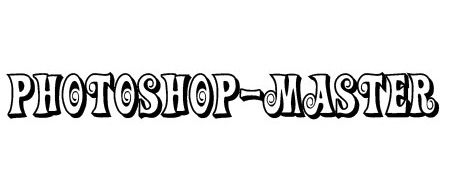
Шрифт супер!
COOOL))))))))))ХД
ХАХА СТИЛЬ РЕТРО!
шикарно!
Респект!
Супер!!!!!!!!!!!!
КЛАСС!!!!
Суперский) Просто офигенный)))
Хороший шрифт! :)
Какой кавай)))
клёва!